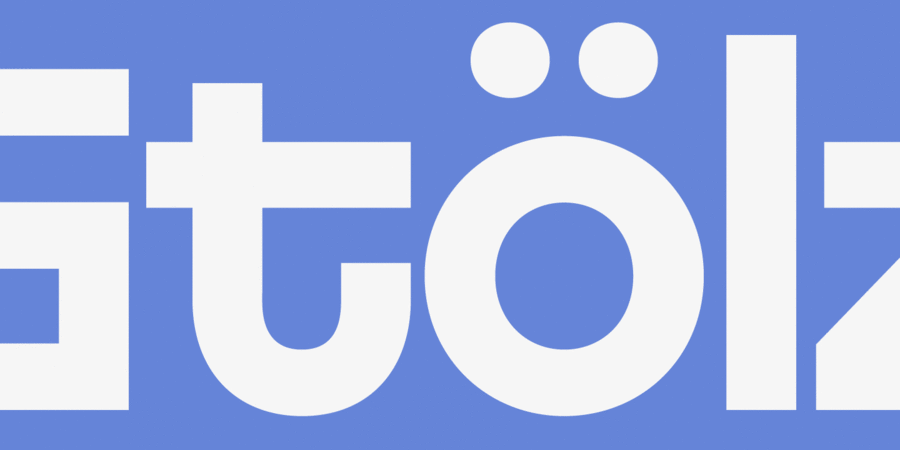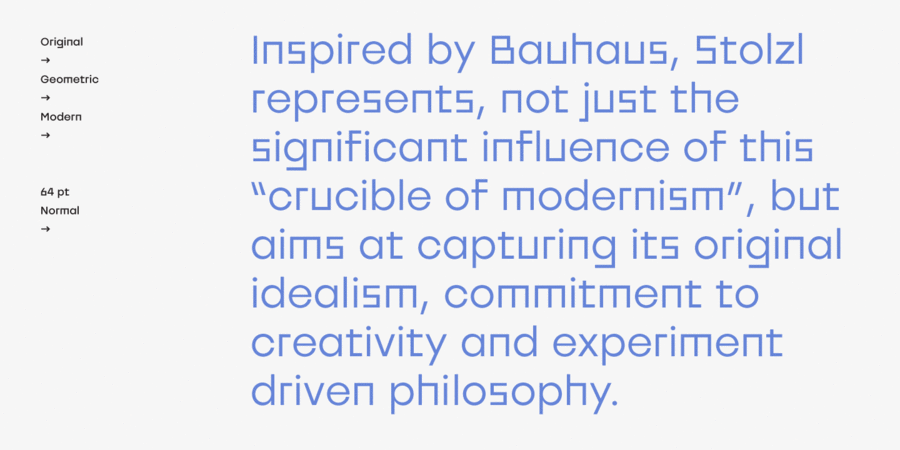
Stolzl Display – це оригінальне шрифтове сімейство, розроблене для заголовків, назв і титрів. Заснована на поєднанні контрастних контурів, гармонія форми і ритму є основою дизайну цього шрифту. Натхненний Баухаузом, Штольцль представляє не тільки значний вплив «тигля модернізму», а й прагне захопити його первісний ідеалізм, прихильність творчості й філософії постійного експерименту. Накреслення включають шість насиченостей, 480 символів з кирилицею, альтернативні ґліфи, ручний кернінг і функції Opentype. Гарнітура названа на честь Ґунти Штьольцль, єдиної жінки-майстра в Баухаузі. Шрифт розробила Марія Пігулевська у 2015 році. Stolzl Display™ є торговою маркою компанії The Northern Block.
6 накреслень
Хіт 1920-х Хіт 1930-х Stolzl Display підтримує 83 мовиУкраїнська, Англійська, Німецька, Польська, Португальська, Іспанська, Французька, Російська, Чеська, Голландська, Італійська, Шведська, Турецька, Фінська, Білоруська, Сербська, Болгарська, Естонська, Литовська, Албанська, Африкаанс, Баскська, Бретонська, Валенсаска, Galician, Гельська (Шотландська), Данська, Індонезійська, Ірландська, Ісландська (Win), Каракалпацька, Каталонська, Норвезька, Окситанська, Ретороманська, Самі Лулі, Тсванська, Узбецька (Лат.), Фарерська, фризька, Чаморро, Естонська (Win), Південносаамська, Албанська (Win), Угорська, Верхньолужицька, Карельська, Латвійська (Mac), Литовська (Mac), Маорійські (Mac), Молдавська (Лат.), Нижньолужицька, Румунська (Win), Словацька, Словенська, Туркменська (Лат.), Хорватська (Win), Естонська (Mac), Курдська, Латишська, Маорійські, Руминська, Абазинська, Аварська, Агульська, Адигейська, Даргинську, Інгуську, Кабардино-Черкеська, Кабардинська, Карачаєво-Балкарська, Кумицька, Лакська, Лезгинська, Македонську, Мордовсько-Мокшанська, Мордовсько-Ерзянська, Ногайська, Рутульська, Табасаранська, Татська, Цахурська, Чеченська Функції сімейства шрифтів Stolzl DisplayЗастосування гарнітури у верстці:
Асоціації з сімейством шрифтів Stolzl DisplayОсобистість і характер гарнітури:
елементарний, ламаний, незграбний, мінімалістичний, точний, рівний, прямокутний, статичний, логічний, лаконічний, стійкий, автоматичний, штучний, холодний, інженерний, міський, різкий, чіткий, креслярський, чистий, сучасний, гострий, тонкий, дротяний, скляний, легкий, прохолодний, ясний, невагомий, прозорий, крихкий, модний, худий, оригінальний, дивний, твердий, надійний, впевнений, сталевий, Простий, машинний, урбаністичний, крижаний, квадратний, експериментальний, дзвінкий, сміливий, рубаний, характерний, незвичайний, цікавий, серйозний, переконливий, залізний, мужній, ностальгічний, тоталітарний, стабільний, гучний, сильний, кондовий, політичний, комуністичний, революційний, пролетарський, індустріальний, техногенний, військовий, армійський, солдатський, грубий, робочий, мотивуючий, залізничний, амбітний, жорсткий, брутальний, ігровий, міцний, важкий, авторитетний, значний, важливий, червоний, монументальний, суворий, блатний, крутий, кричущий
креслення, дизайн, лосьйон, туалетна вода, мода, небо, конструктор, архітектура, урбаністика, коворкінг, Місто, інтер'єр, гра, анімація, електроніка, війна, армія, зброя, машинобудування, прапор, мітинг, політика, шахта, завод, металургія, верстат, інструмент, будівництво, будматеріали, тара, склад, порт, ящик, патрони, техніка, промисловість, електростанція, енергетика, ремонт, депо, шахтар, шолом, уніформа, вагон, авіація, літак, страйкбол, взуття, залізниця, робочий, страйк, Протест, кубики, лего, розваги, танк, тренажери, революція, блокбастер, бойовик, екшен, цегла, вантажівка, далекобійник, мотор, двигун, реп, концерт, селфі, головокрутка Гарнітура має ознаки стилів: